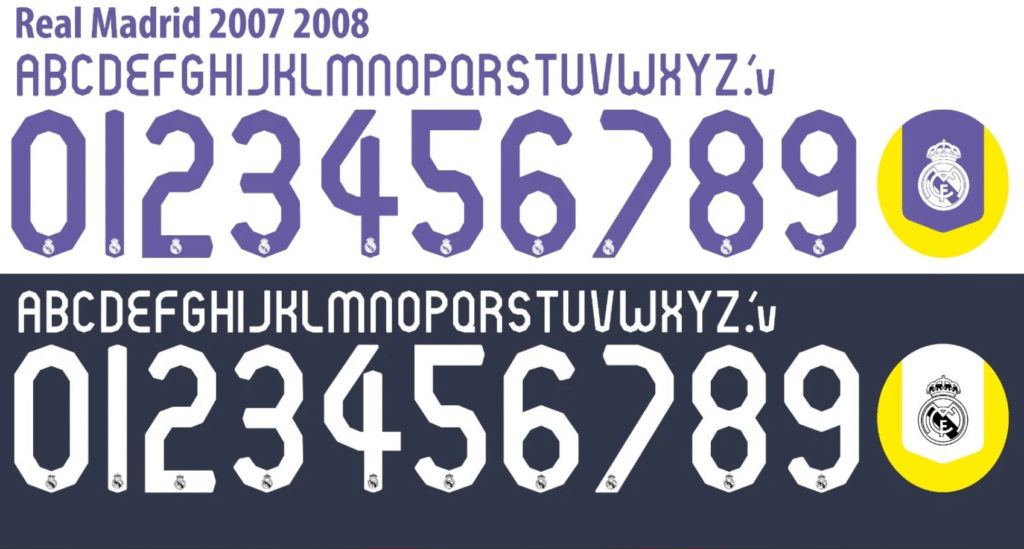
Reviva uma das temporadas mais dominantes da história dos Merengues. A temporada 2007-2008 foi marcada pela conquista do 31º título de La Liga com uma campanha sólida sob o comando de Bernd Schuster. Foi o ano em que lendas como Raúl, Van Nistelrooy, Robinho, Sneijder e Casillas brilharam nos gramados do Santiago Bernabéu.
Estilo Visual e Identidade
A tipografia do Real Madrid na temporada 07/08 se destaca pela sua legibilidade e elegância clássica. Diferente das fontes futuristas e angulares de anos posteriores, este design da Adidas aposta em números mais arredondados e letras com espessura média, transmitindo uma sobriedade que combinava perfeitamente com o uniforme branco “limpo” daquela época.
Nos uniformes titulares, a fonte era aplicada geralmente na cor preta ou roxa (em alusão à faixa de Castela), criando um contraste forte e tradicional. É uma fonte indispensável para colecionadores que desejam recriar a mística dos “Galácticos” em sua fase de transição.